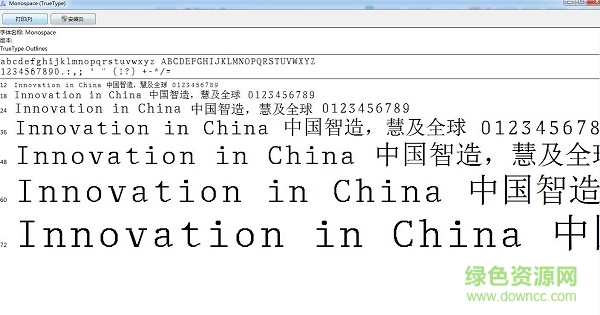
monospace是什么字體?這是一款適用于win7和linux系統(tǒng)的英文等寬字體,字符寬度相同,適用于電子顯示器領(lǐng)域,一般的word軟件里就有monospace字體,歡迎大家免費(fèi)下載!
等寬字體的應(yīng)用
由于等寬字體的特點(diǎn),當(dāng)今的平面設(shè)計(jì)上也有特意使用等寬字體所具有的文化特征進(jìn)行創(chuàng)作的風(fēng)格,其中最具有代表性的就是ASCII藝術(shù)。ASCII藝術(shù)所使用的字符都是等寬字體,如果改用比例字體,圖片往往變形而無法表達(dá)創(chuàng)作者本意。